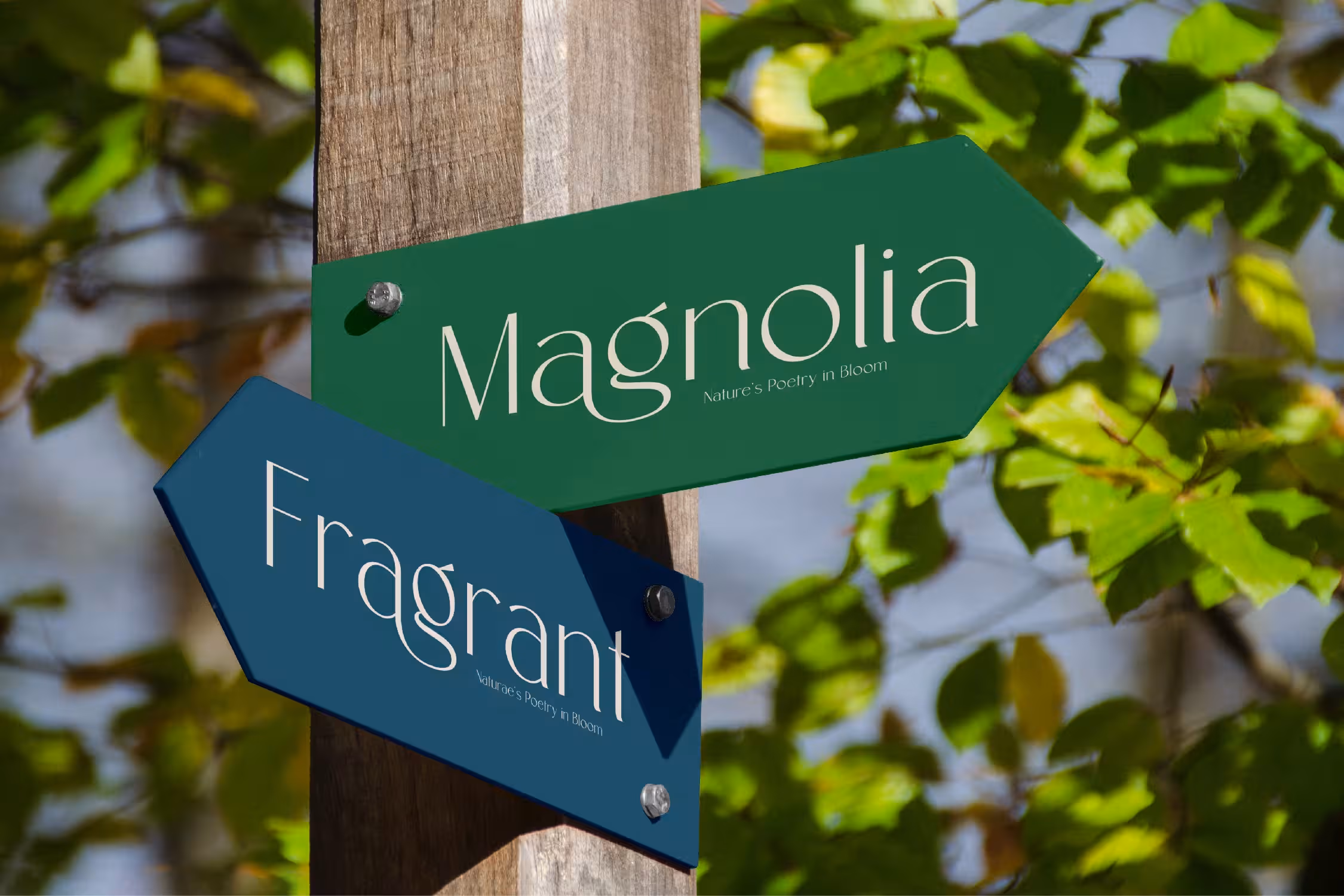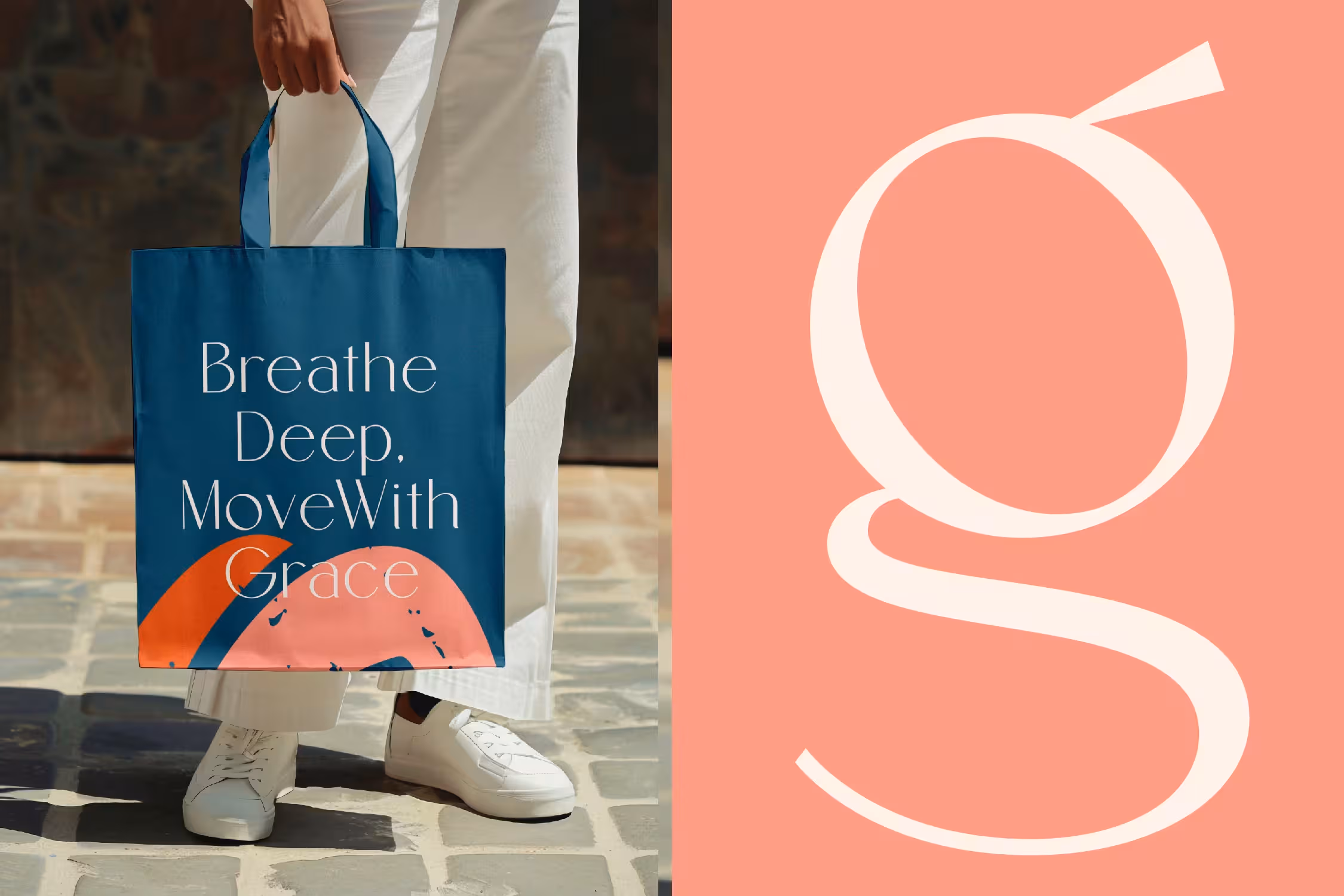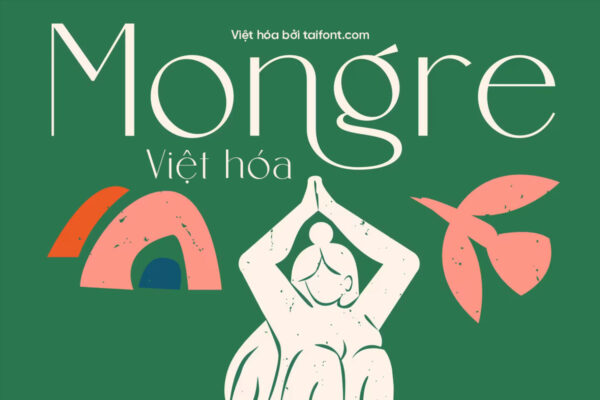
Giới thiệu Combo Font TF Mongre Regular & Italic Việt hóa
Bộ đôi TF Mongre Regular & Italic Việt hóa là những font chữ không chân (sans-serif) nổi bật với vẻ đẹp thanh mảnh, hiện đại và tinh tế. Với thiết kế gọn gàng, đường nét sắc sảo nhưng vẫn giữ được sự mềm mại, combo này mang đến phong cách sang trọng và tối giản.
1. TF Mongre Regular Việt hóa: Là phiên bản thẳng (regular) của font, với độ dày nét vừa phải, đảm bảo tính dễ đọc và sự chuyên nghiệp. Font này phù hợp cho:
- Thiết kế thương hiệu: Tạo logo, nhận diện thương hiệu mang phong cách tối giản, hiện đại và cao cấp.
- In ấn: Hoàn hảo cho các tài liệu báo cáo, sách, tạp chí hoặc các ấn phẩm cần sự rõ ràng và tinh tế.
- Túi vải, bao bì: Đảm bảo thông tin rõ ràng, dễ đọc trên sản phẩm, thể hiện sự cao cấp của thương hiệu.
2. TF Mongre Italic Việt hóa: Là phiên bản nghiêng (italic), mang đến sự mềm mại, bay bổng và linh hoạt hơn. Phiên bản này lý tưởng để:
- Tạo điểm nhấn: Dùng cho các câu trích dẫn, lời tựa, hoặc các phần văn bản cần sự khác biệt, nhấn mạnh.
- Thiết kế thời trang: Thêm nét cá tính, uyển chuyển cho các nhãn mác, bao bì sản phẩm thời trang.
Sức mạnh của Combo:
Khi kết hợp, TF Mongre Regular và Italic tạo nên một cặp đôi hoàn hảo, cho phép bạn đa dạng hóa thiết kế mà vẫn giữ được sự đồng bộ về phong cách. Mongre Regular có thể dùng cho các tiêu đề chính, thông tin quan trọng, trong khi Mongre Italic sẽ làm nền hoặc điểm nhấn cho các chi tiết phụ, lời kêu gọi hành động hoặc những phần cần sự mềm mại, độc đáo.
Bộ đôi này sẽ giúp bạn tạo ra những thiết kế không chỉ đẹp mắt mà còn rất chuyên nghiệp và đầy phong cách.